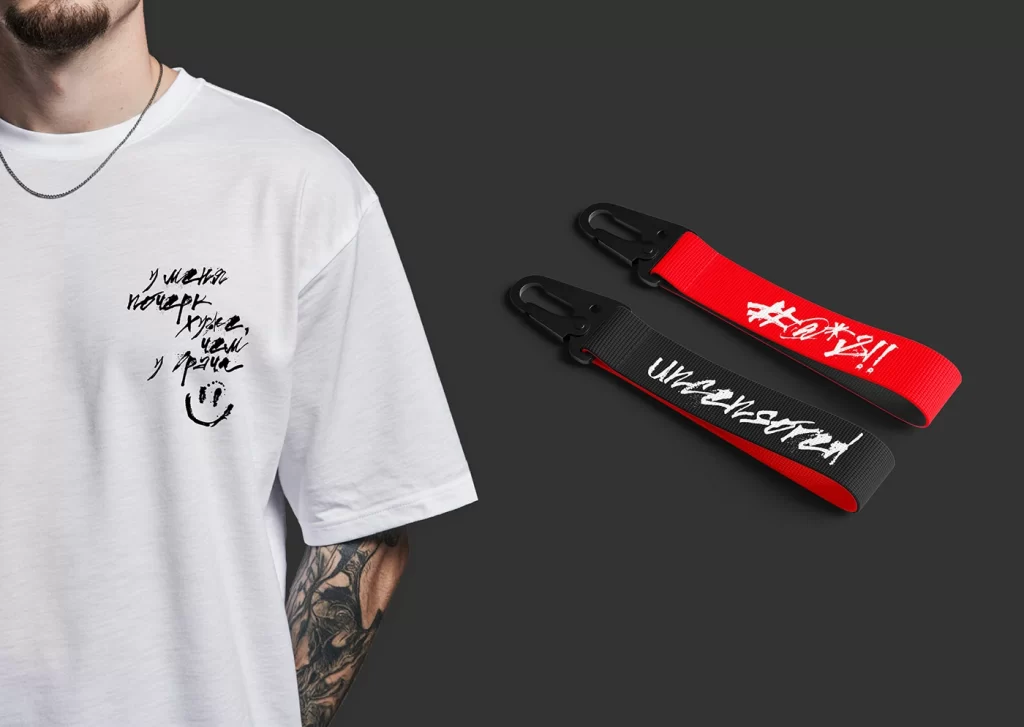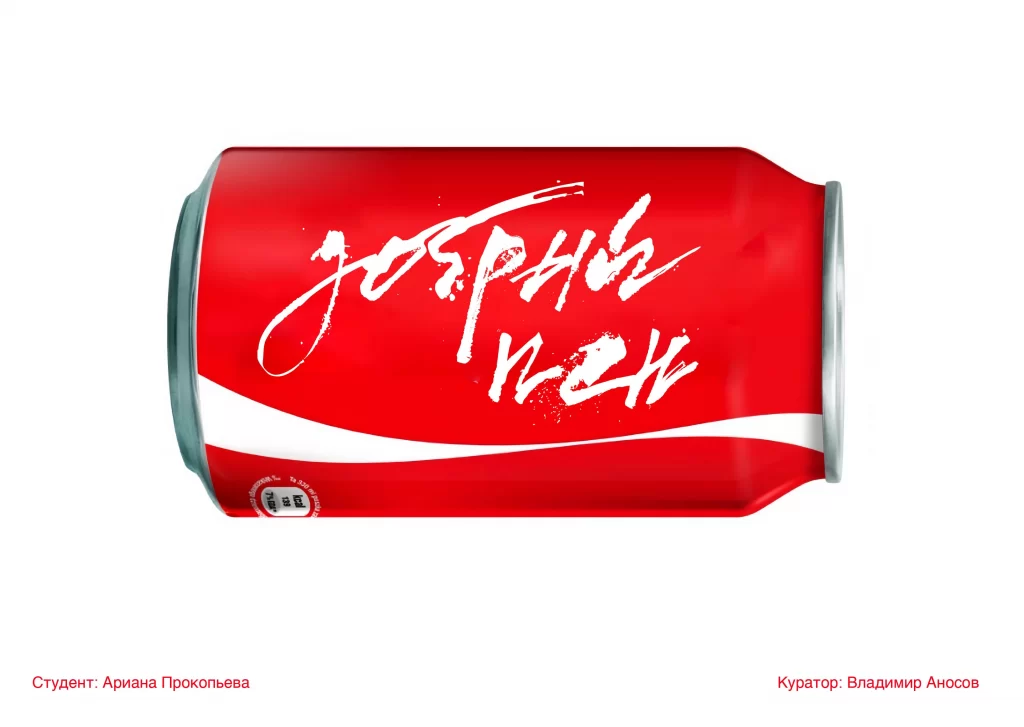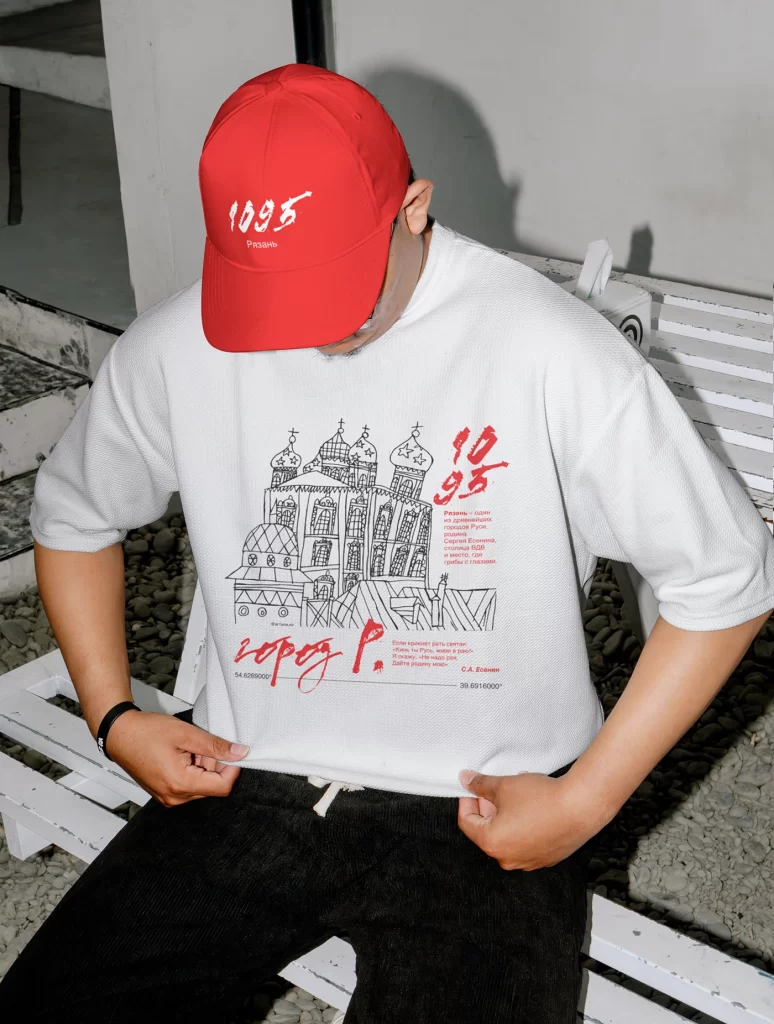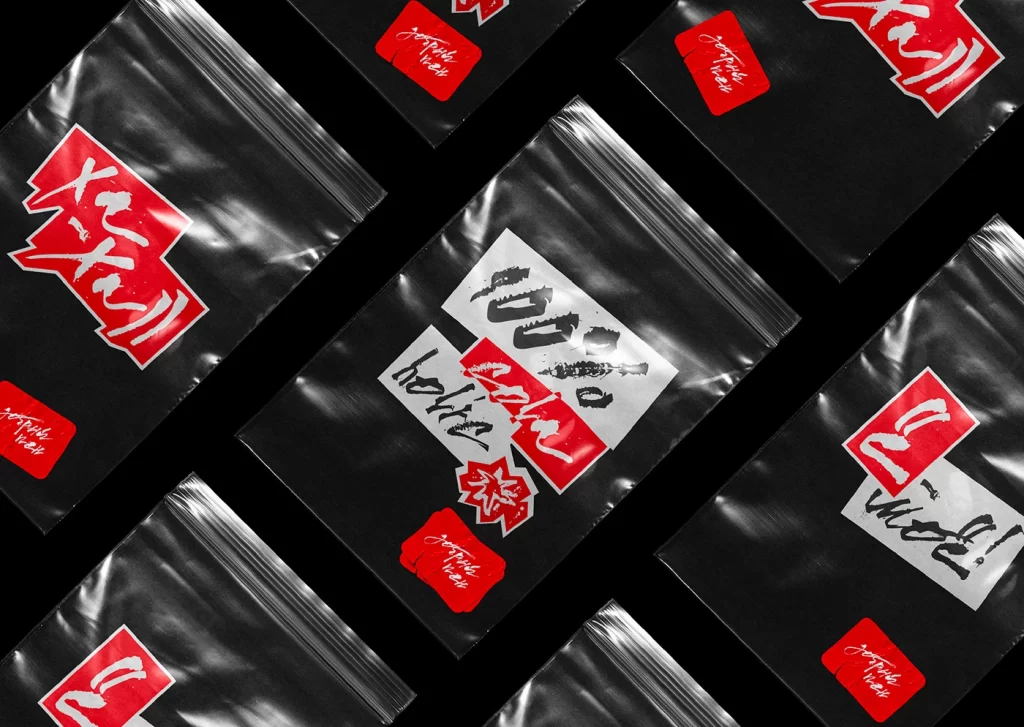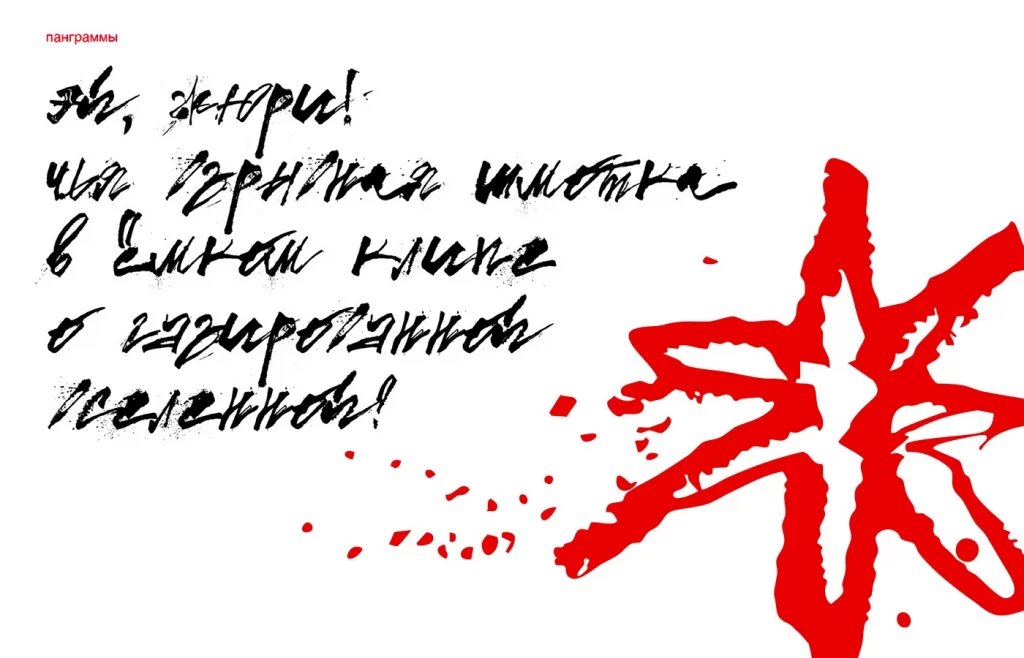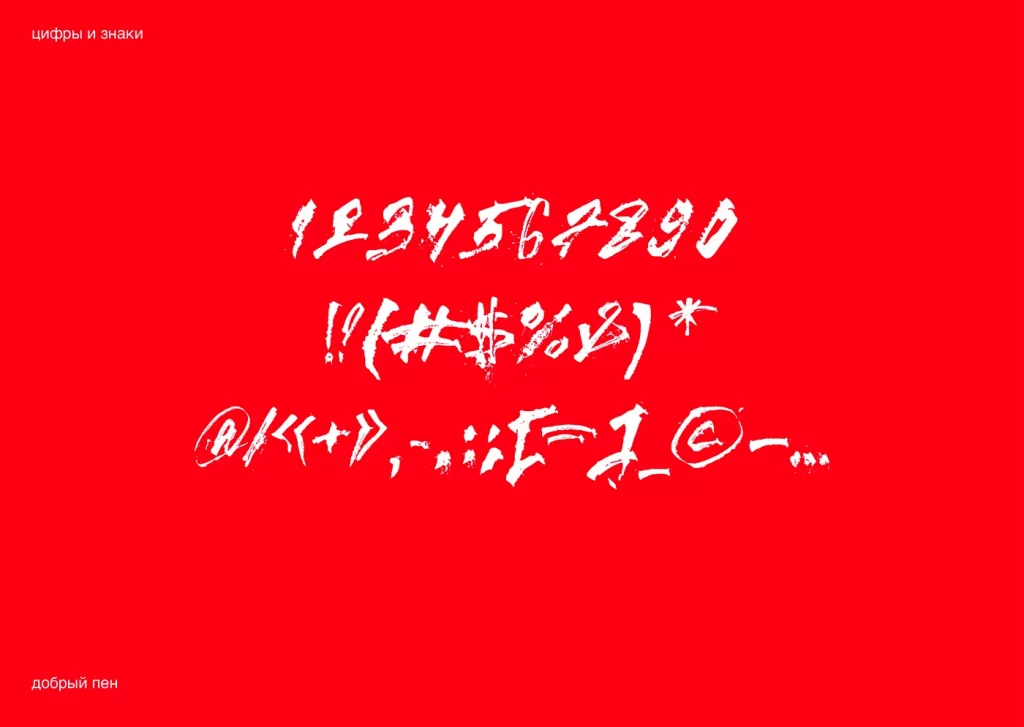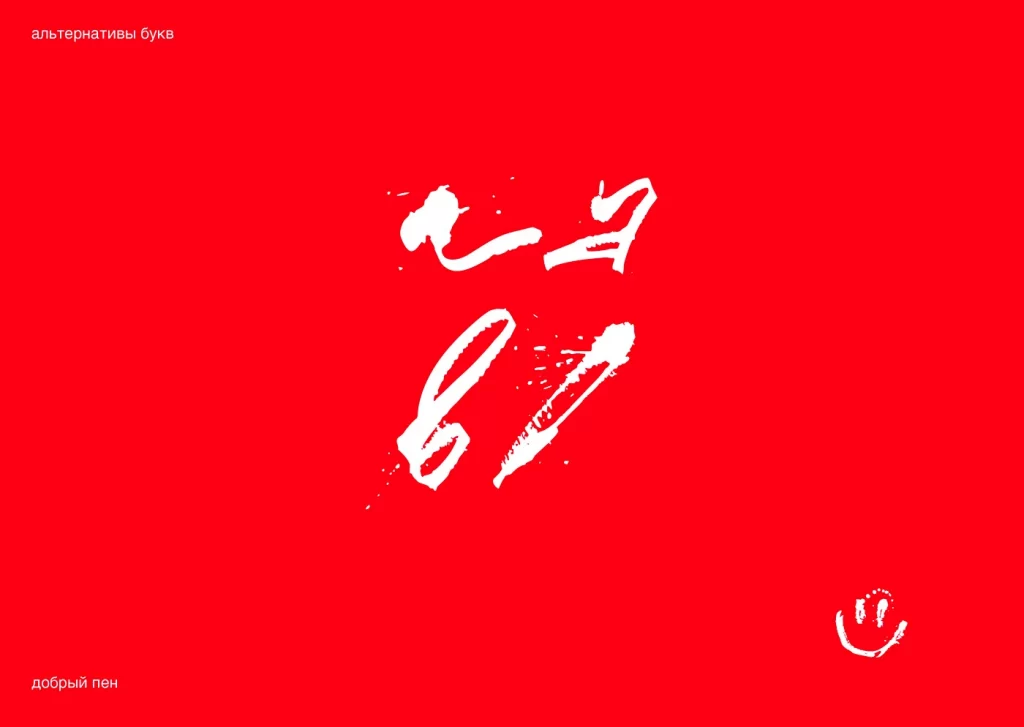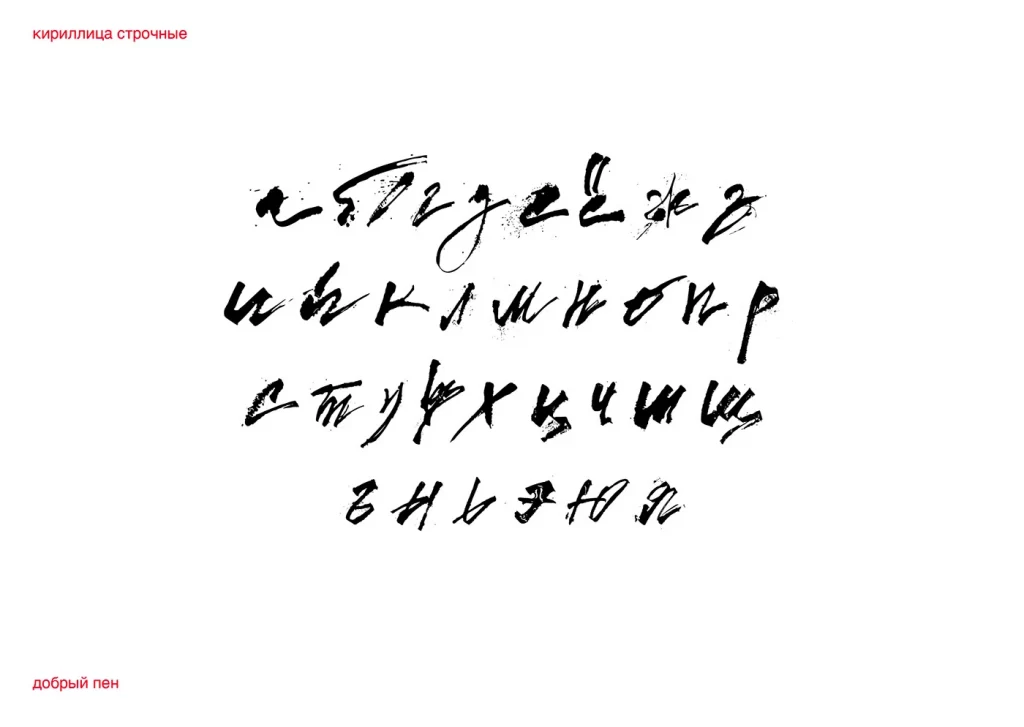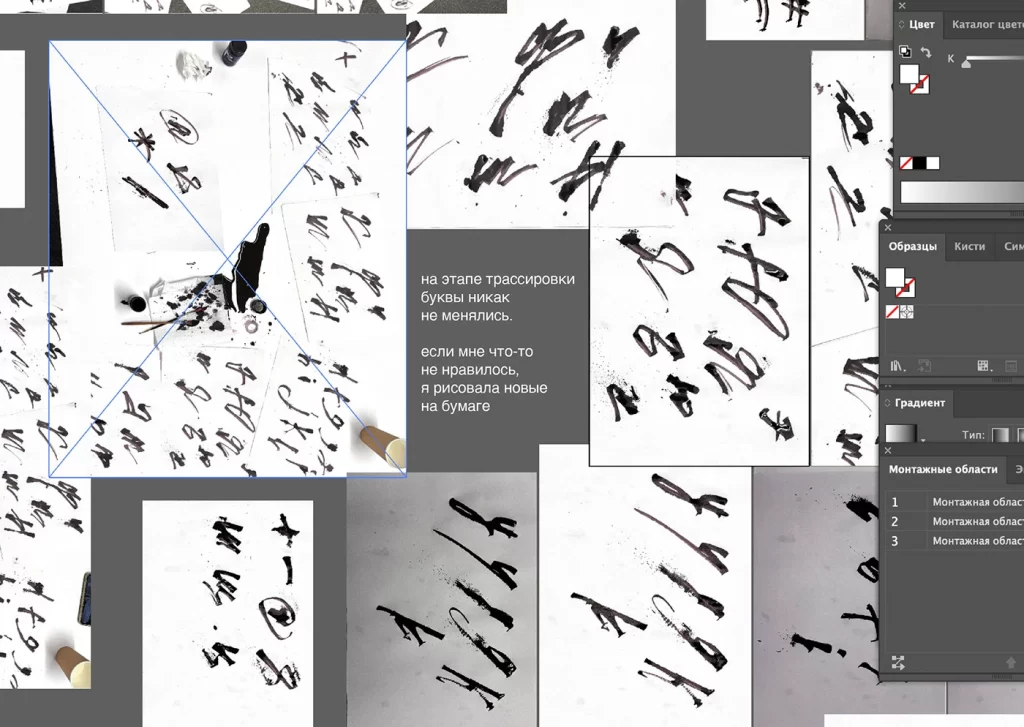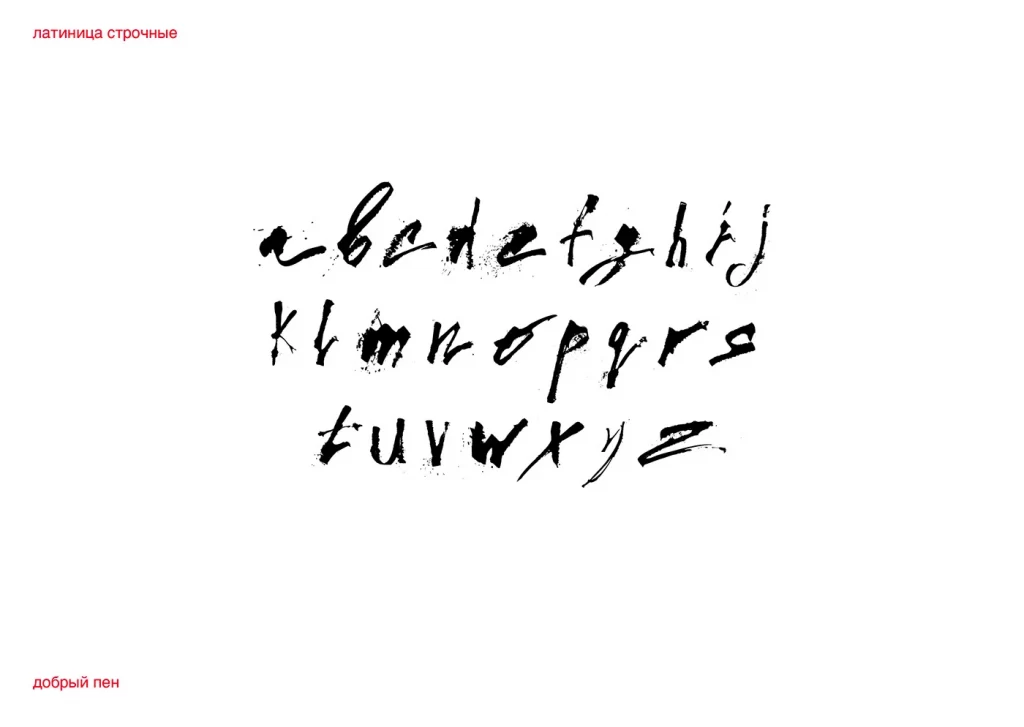
Dobry Pen — рукописный шрифт создан за один вечер
Dobry Pen (Добрый пен) — выразительный рукописный шрифт от дизайнера из Питербурга Арианы Прокопьевой, вдохновленный письмом кола-пером (Cola Pen). Его неровные линии, естественные перепады толщины и легкая небрежность создают ощущение текста, написанного вручную, сохраняя при этом хорошую читаемость.
Шрифт отлично передает атмосферу творчества и свободы, благодаря чему подходит для проектов, где важно подчеркнуть индивидуальность и живой характер оформления. Он гармонично смотрится в заголовках, постерах, обложках, открытках, упаковке, логотипах, фирменном стиле, публикациях в социальных сетях и рекламных материалах.
Особенности Dobry Pen:
• естественная имитация письма;
• выразительные мазки с контрастной толщиной линий;
• динамичный и дружелюбный характер;
• поддержка кириллицы и латиницы;
• хорошо сочетается как с минималистичными, так и с декоративными шрифтами.
Dobry Pen станет отличным выбором для дизайнеров, иллюстраторов и всех, кто хочет добавить макетам ощущение ручной работы и авторского почерка. Он одинаково эффектно выглядит как в крупных заголовках, так и в коротких акцентных надписях, придавая композиции теплую и непринужденную атмосферу.